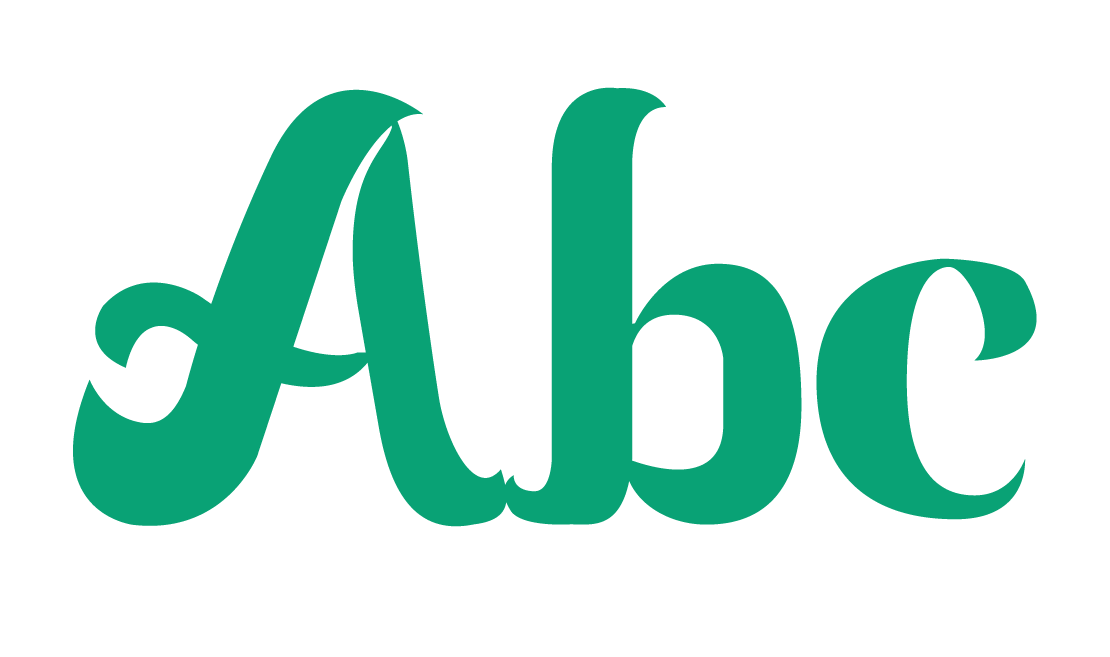
Elección 2010: Tipografía Gratis de junio
Es tiempo de que ahora el respetable tenga la oportunidad de elegir a la tipografía gratis de la temporada, por lo cual en breve podran ver una encuesta desde la cual podrán votar, y ahora lo más importante de una elección, las candidatas…
1.- Chancla Bastarda
Prima hermana de la ya conocida Memela Fraktur, hereda sus terminaciones redondeadas, pero ahora es más ruda y afrancesada tomando lo mas peor de esos peligrosos monsatrios medievales.
2.- Rododendro
Basada en la primer tipografía que hice, con elementos organicos y ligeros, haciendola más bonachona.
3.- Musa Ornata
La versión itálica de la ya afamada Musa paradisiaca, cuenta al igual que su contraparte regualr con un amplio set de mayúsculas alternativas, entre las que sobresalen las «Swash caps» basadas en logotipos de grupos de música tropical.
• Si aún no los convencen con los carateres presentados, en lo que se vota se iran presentando diferentes palabras o frases compuestas con estas fuentes